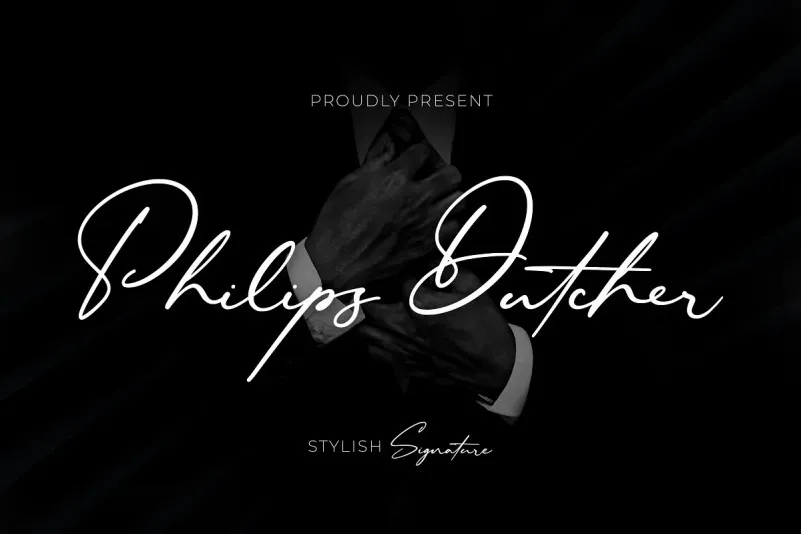
Philips Dutcher Font – Fonte Grátis
Philips Dutcher Font
A Philips Dutcher Font é uma elegante e moderna tipografia de escrita feita pelo Almarkha Type. Inspirada no estilo do script casual e rápido, essa fonte contém 41 ligaturas meticulosamente desenhadas por mãos humanas. As letras são criadas a partir da impressão em papel, posteriormente scansadas e convertidas para o formato vetorial com cuidado. Esta fonte é perfeita para quem procura uma maneira única de dar um toque diferenciado aos seus projetos digitais sem perder seu charme único. Com sua aparência moderna e elegante, a Philips Dutcher Font pode ser usada em anúncios, design gráfico e até mesmo em criações de conteúdo para redes sociais, oferecendo uma aposta segura no visual interessante que tanto adoramos nas nossas mídias digitais.